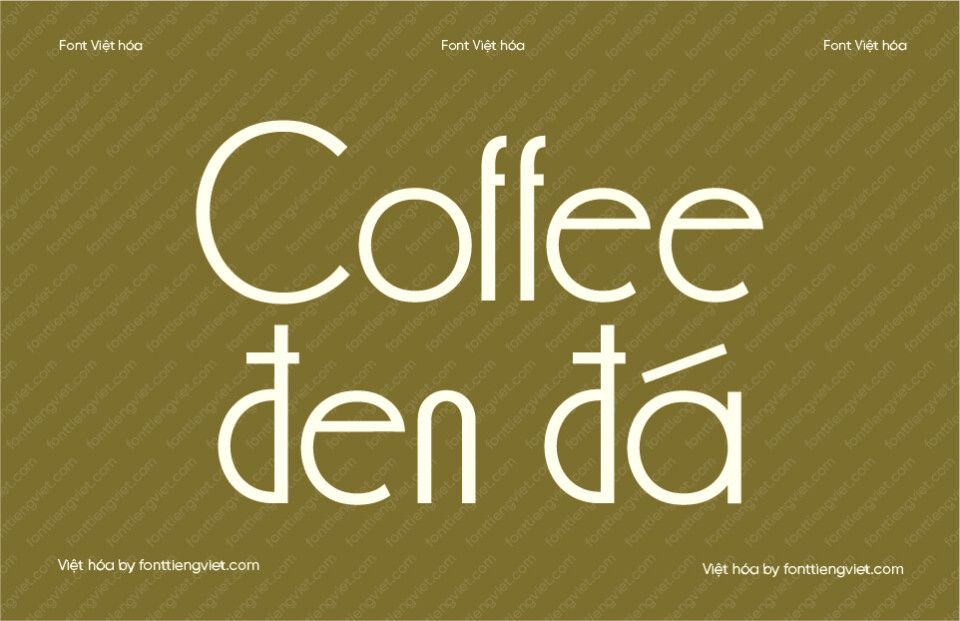
Giới thiệu về Font Việt hóa 1FTV VIP Decoment
Trong thế giới thiết kế đồ họa hiện đại, việc lựa chọn một bộ Font Chữ phù hợp đóng vai trò quyết định đến tính thẩm mỹ của sản phẩm. Font Việt hóa 1FTV VIP Decoment nổi lên như một giải pháp hoàn hảo cho những ai đang tìm kiếm sự kết hợp giữa nét cổ điển và hơi thở đương đại. Đây là bộ phông chữ được tinh chỉnh kỹ lưỡng, hỗ trợ đầy đủ bảng mã tiếng Việt giúp người dùng không còn lo lắng về lỗi gõ dấu hay hiển thị sai ký tự. Với phong cách thanh lịch và sang trọng, bộ font này cực kỳ phù hợp cho các bạn học sinh, sinh viên thực hiện báo cáo hoặc giáo viên thiết kế bài giảng điện tử sinh động hơn.
Đặc điểm nổi bật của Font Việt hóa 1FTV VIP Decoment
Bộ Font Việt hóa 1FTV VIP Decoment sở hữu những đường nét mảnh mai nhưng vẫn giữ được sự chắc chắn trong từng khung chữ. Cấu trúc của font được lấy cảm hứng từ các dòng chữ trang trí nghệ thuật, mang lại cảm giác chuyên nghiệp cho mọi bản thiết kế. Điểm đặc biệt nhất chính là khả năng hiển thị sắc nét trên cả màn hình kỹ thuật số lẫn bản in giấy. Điều này giúp các ấn phẩm như thiệp mời, bìa sách hay poster sự kiện nhà trường trở nên thu hút và có điểm nhấn riêng biệt hơn so với các phông chữ hệ thống thông thường.
Ứng dụng và cách sử dụng font hiệu quả
Để tận dụng tối đa vẻ đẹp của Font Việt hóa 1FTV VIP Decoment, người dùng nên kết hợp nó với các màu sắc trung tính hoặc tông màu pastel nhẹ nhàng. Trong môi trường giáo dục, font này có thể dùng để làm tiêu đề bài học hoặc trình bày các câu trích dẫn truyền cảm hứng trên bảng tin lớp học. Việc cài đặt cũng rất đơn giản, chỉ cần tải về và sao chép vào thư mục font của máy tính là bạn có thể sử dụng ngay trên Word hay PowerPoint. Hy vọng bộ Font Miễn Phí, Font Việt Hóa, Font Việt hóa 1FTV VIP Decoment này sẽ là nguồn cảm hứng mới cho các dự án sáng tạo của bạn trong tương lai.